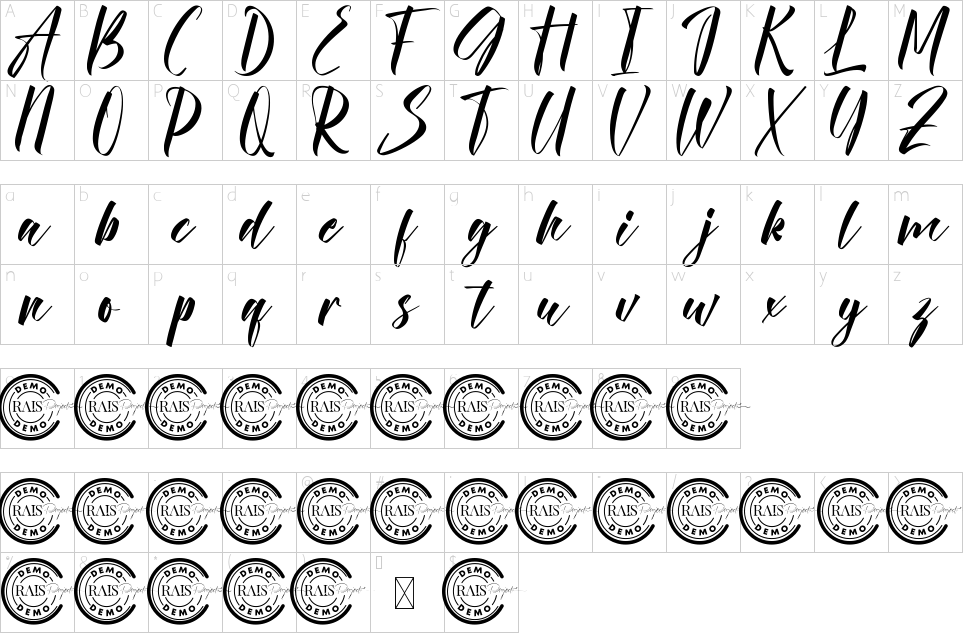
A fonte ‘Saviour Tasted’ é um recurso gráfico gratuito que oferece uma variedade de estilos únicos e leves, ideal para qualquer projeto que precise de uma fonte agradável e versátil. Desenvolvida pelo RaisProject, esta fonte é uma excelente opção para quem busca qualidade sem gastar recursos financeiros. Com seu design limpo e elegante, a ‘Saviour Tasted’ é perfeita para uso em sites, aplicativos, logotipos ou qualquer outro projeto digital. Sua facilidade de uso e variedade de estilos garantem que ela seja uma fonte que atenda a todas as suas necessidades. Até agora, a fonte foi baixada 743 vezes, evidenciando seu valor e qualidade. Sua disponibilidade gratuita torna ‘Saviour Tasted’ uma escolha inteligente para aqueles que procuram um recurso gráfico de qualidade sem precisar gastar. Descubra por si mesmo como esta fonte pode transformar o visual de seu próximo projeto.